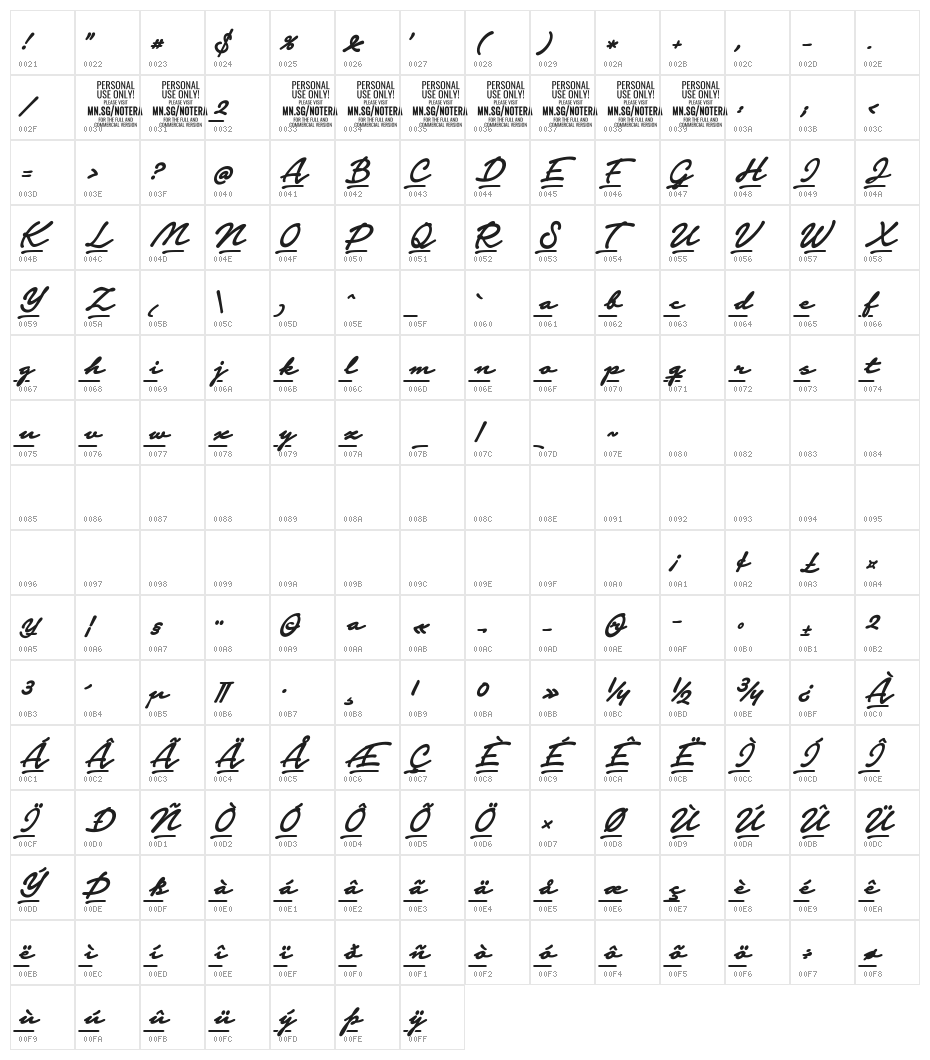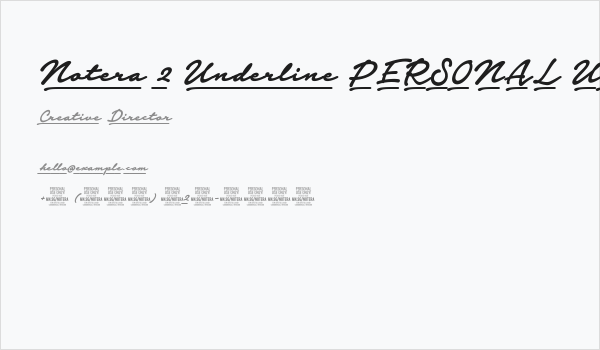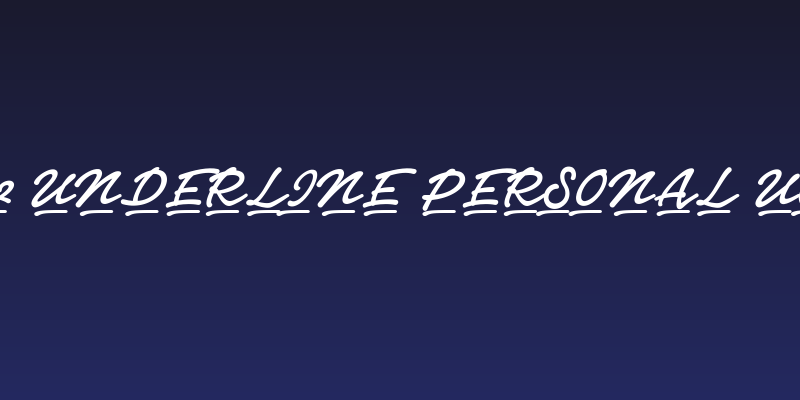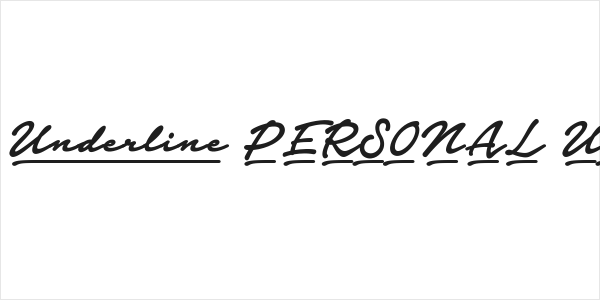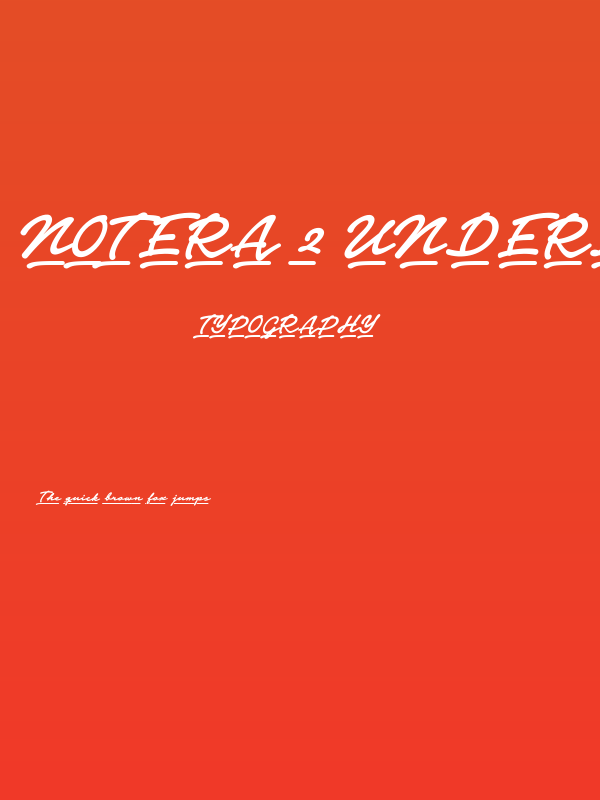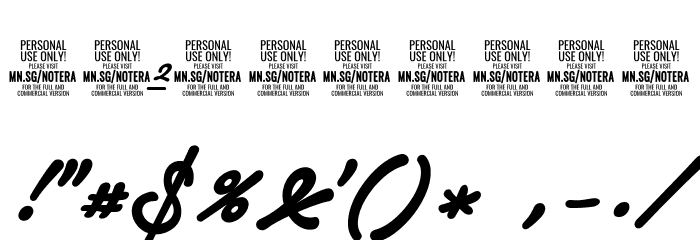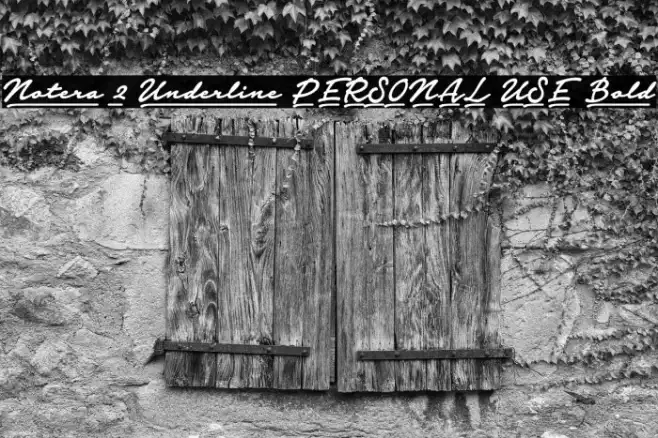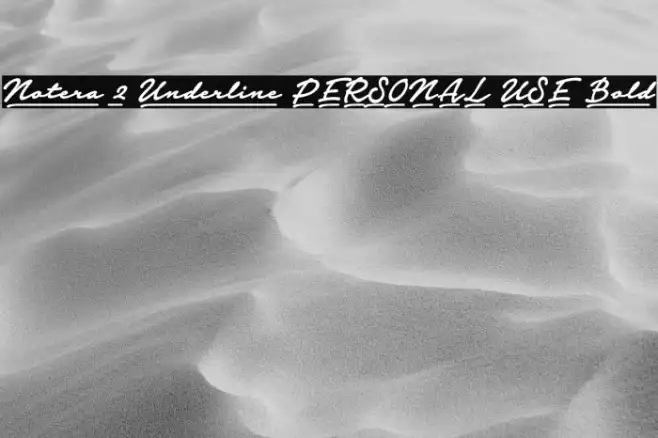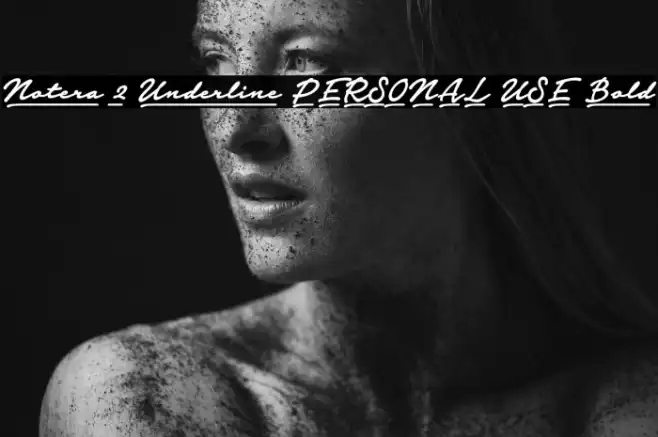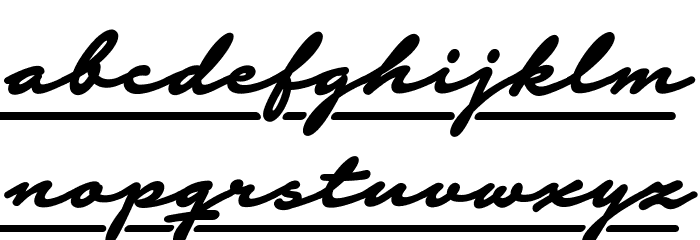
Notera 2 Underline PERSONAL USE Bold Font
| Cas d'utilisation | Logos, Headlines, Invitations |
| Projets proposés | Ideal for branding, logos, invitations, and any design project that requires a bold and elegant touch. |